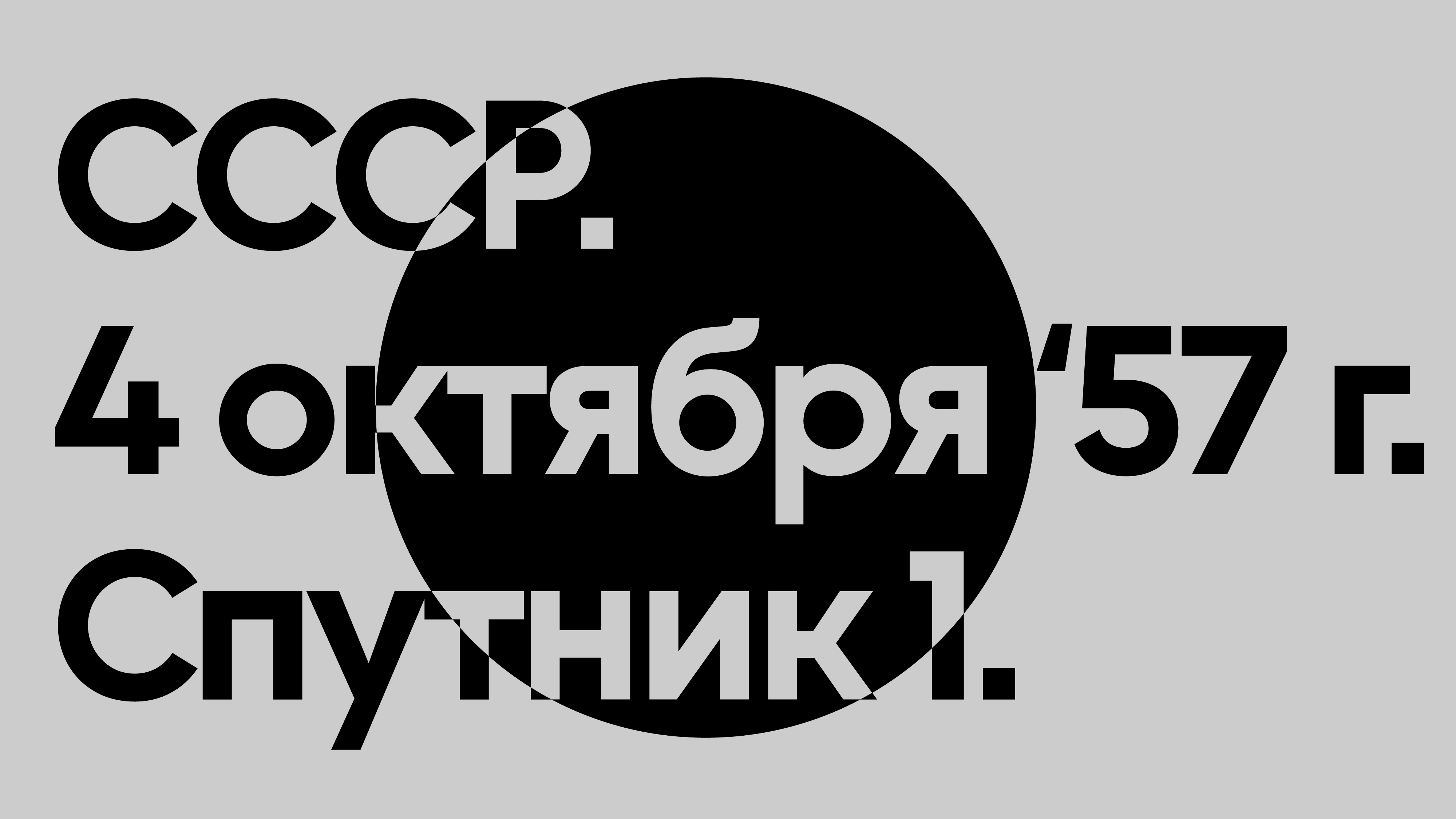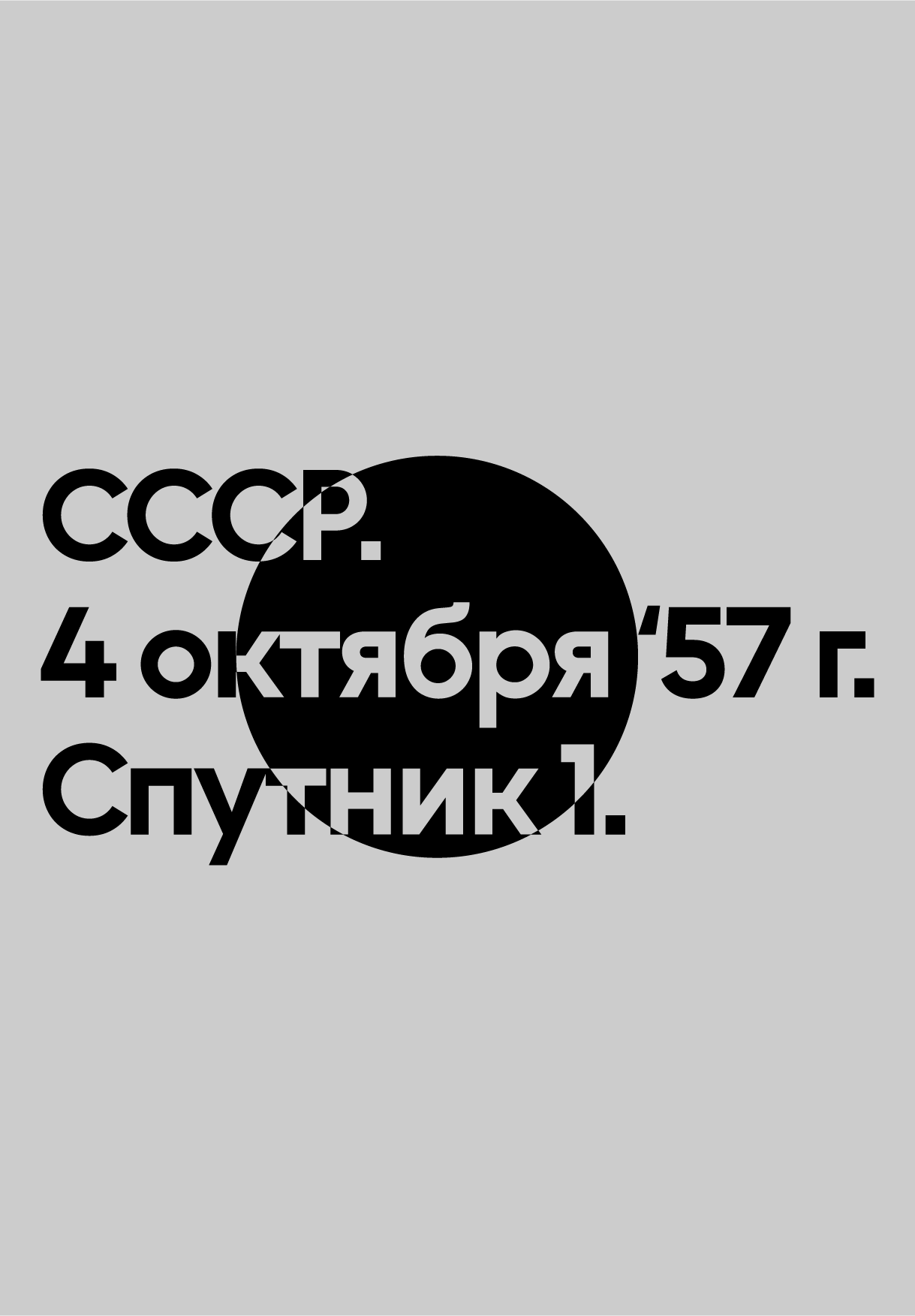
F37 Moon Cyrillic Font Sampler
F37 Moon имеет большую высоту по оси X, что придает ему ультрачистый и ультраминималистичный вид. Короткое тело шрифта создает компактный и смелый вид.